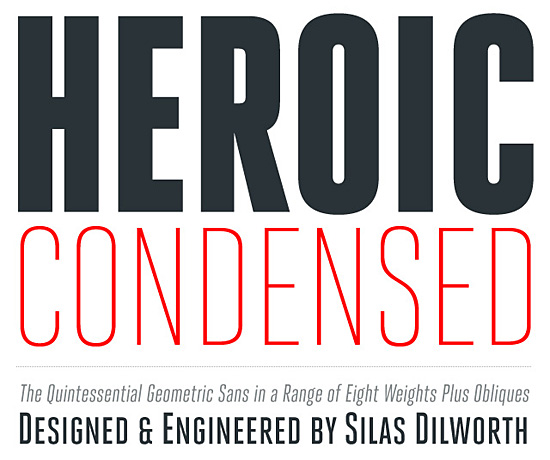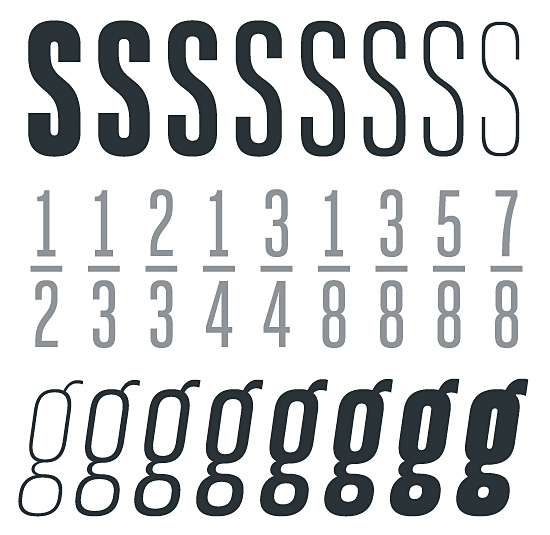
Heroic Condensed (TypeTrust)
Heroic Condensed is the graphic embodiment of the idealized, no-nonsense, narrow grotesque. From poster design to editorial layout, Heroic Condensed is intended for a range of uses – a worthy addition to any designer’s font collection.
Not just a quickly generated spin-off of a text family, Heroic Condensed has been crafted from scratch with a structural logic of its own: a fusion of pure geometry and optical balance. At its core you will find a geometric skeleton, but mathematics alone does not make attractive type. Heroic Condensed has been honed by and for the acute and sublime workings of the human eye. The finest adjustments have been applied to every curve and every angle of its letterforms for even color and visual equality across a versatile range of eight weights. Even regarding usability, Heroic Condensed exhibits technical refinement. With careful attention paid to the economy of metrics, the need for extensive kerning tables has been alleviated by a hand-tuned matrix of sidebearings in conjunction with already streamlined glyph designs.
Heroic Condensed is further bolstered with Opentype Small Caps, Tabular Figures, Fractions, and the standard TypeTrust character set which includes a full array of Latin diacritics.
Die ist aber schon arg nah an der Folio dran…
Bei solchen Headline-Fonts lassen sich Ähnlichkeiten
einfach nicht vermeiden. Die Heroic unterscheidet
sich in etlichen Details trotzdem deutlich von der Folio -
dazu ist sie besser ausgebaut und auf dem Stand
der Zeit!
jaja schon klar, mich amüsieren nur die heroischen Worte mit denen sie angepriesen wird … has been crafted from scratch usw. …
das typische blabla eben ... aber ich finde die heroic
trotzdem ganz schick und eine korrekte alternative
zu schlecht ausgebauten headlineschriften wie der folio
oder der trade gothic condensed.
was sagt ihr?
gefällt mir. ich bin vor allem überrascht, wie gut sich die kapitälchen machen. die sind bei solchen schriftarten ja recht selten, wenn ich mich nicht irre.
schlecht finde ich, dass es zu ungewöhnlichen zeichenformen keine neutralen alternativen gibt, zum beispiel für die g-minuskel oder das @ im geschlossenen kreis. so was erschwert mir kaufentscheidungen immer, auch wenn ich beim ersten einsatz feststelle, dass die neutrale variante langweilig ist, und nur noch die andere benutze. außerdem mag ich es nicht, wenn buchstaben mit ihren diakritika (beinahe) kollidieren, siehe ›?‹ in fast allen schnitten.
das war mir gar nicht aufgefallen und ist in der tat ein
argument was gegen die heroic spricht. das keine
alternative fürs @ angeboten wird ist echt ärgerlich ...
das @ finde ich eigentlich ganz nett, eine alternative wäre trotzdem schön. sind wir schon verwöhnt?
das ausrufezeichen in keilform finde ich eher etwas unangenehm. das ? ist je eher der ausnahmefall, damit könnte ich leben. im großen und ganzen trotzdem eine sehr schöne schrift und bei dem preis von 160 $ für die ganze familie sollte man wirklich überlegen ob man zuschlägt oder nicht. leider brauche ich im moment keinen headlinefont suche eher was serifiges in richtung dolly was gut zur national passt.
auch eine schrift, die ich wegen eines buchstabens nicht kaufen mag. sieht einfach zu …
… aus. finde ich.
mit dem ausrufezeichen der heroic hab ich
keine probleme. da stören mich eher
die form der anführungen und ähnlicher
zeichen ...